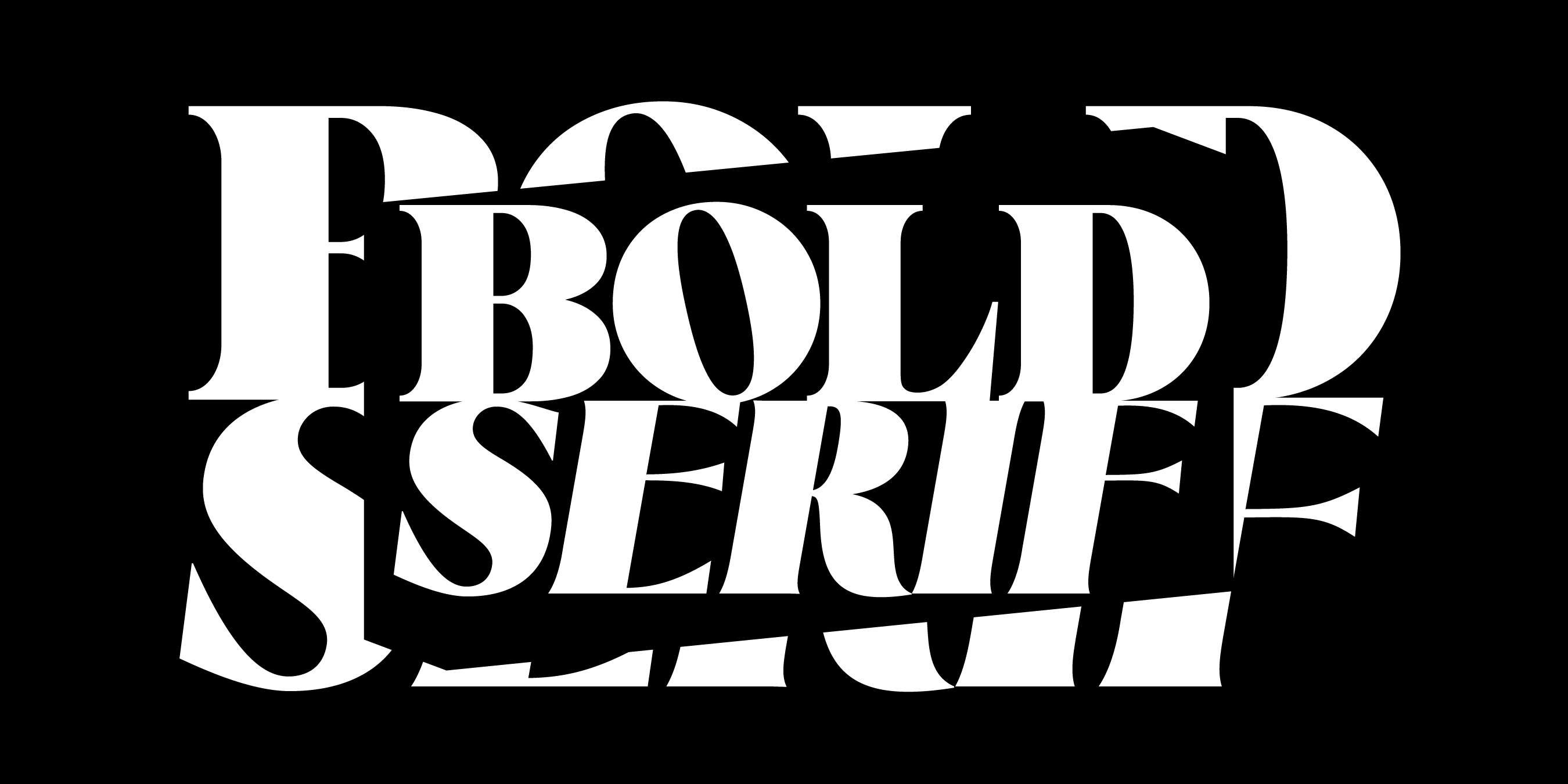
Wo Serifen stark sind: Diese fetten Serifenschriften stehlen allen die Show
Where Serifs Stand Strong: Bold Serif Fonts That Steal The Show
In den letzten Jahren hat die Designwelt eine bemerkenswerte Wiedergeburt von Serifenschriften erlebt, die durch das Aufkommen des Maximalismus im Design beschleunigt wurde. Diese Wiederbelebung ist nicht einfach eine nostalgische Rückkehr zur Tradition, sondern ein strategisches Engagement für Persönlichkeit und Ausdruckskraft in der Typografie. Serifenschriften mit ihren charakteristischen „Füßen“ am Ende der Buchstaben bieten eine breite Leinwand für die Darstellung von Charakter – dank ihrer unterschiedlichen Formen und Umrisse können sie ein breiteres Spektrum an Tönen vermitteln als serifenlose Schriften .
Die einzigartigen Merkmale jeder Schriftart mit fetten Serifen können ihnen eine große Wirkung verleihen. Sie sind so konzipiert, dass sie den Raum selbstbewusst einnehmen und sowohl dominant (weil sie mehr Leerraum einnehmen) als auch nuanciert (weil sie mehr Zeilen zum Arbeiten haben) in ihrem Ausdruck sein können. Diese Schriftarten können von weich und bauschig reichen, was Wärme und Zugänglichkeit ausstrahlt, bis hin zu scharf und stark, was Selbstvertrauen und Solidität ausstrahlt. Diese Vielseitigkeit macht Schriftarten mit fetten Serifen zu unverzichtbaren Werkzeugen für Designer, die ihrer Arbeit Persönlichkeit verleihen möchten.
Während minimalistische serifenlose Schriftarten aufgrund ihrer Einfachheit im Fließtext weiterhin beliebt sind, glänzen fette Serifenschriften in Rollen, die Aufmerksamkeit erregen. Ob in Überschriften, Buchtiteln, Zitaten oder jedem Designelement, das hervorstechen soll, fette Serifen geben ein autoritäres Statement ab. Sie dienen als emotionaler Brennpunkt, ziehen den Blick des Betrachters auf sich und verankern die visuelle Hierarchie einer Komposition.
In einer Landschaft, in der Design nach einem Gleichgewicht zwischen Wirkung und Eleganz sucht, bieten fette Serifenschriften ein kraftvolles Medium für den kreativen Ausdruck und sorgen dafür, dass Botschaften nicht nur gesehen, sondern auch gefühlt werden.
In dieser Liste untersuchen wir zehn fette Serifenschriften aus unserem Schriftstudio, die diese Prinzipien verkörpern. Jede ausgewählte Schriftart kann ein Statement abgeben, eine Nische besetzen und Ihrem Design mehr Tiefe verleihen.
1. Edde, moderne Craft-Serife mit starken Schnitten
Edde, moderne Craft-Serif mit starken Schnitten
Neueste Serifenschrift in unserer Sammlung: Edde in fetteren Stärken wie Bold, Extrabold und Black.
2. Kontrast Soft mit runden Rundungen für einen flauschigen Look
Contrast Soft mit runden Rundungen für einen flauschigen Look
Bauhaus Soft in Schwarz.
3. Kijs Extrabold für einen organischen, weichen Stil
Kijs Extrabold für einen organischen, weichen Stil
Kijs in Extrafett.
4. Quil, moderne Schriftart mit kurzen Serifen
Quil, moderne Schriftart mit kurzen Serifen
Bauhaus Quil in Fettschrift.
5. Rozi mit scharfen, langen Serifen
Rozi mit scharfen, langen Serifen
Bauhaus Rozi in Extrabold.
6. Mod für ein zeitloses, klares Design
Bauhaus Mod für moderne Serifen
Bauhaus Mod in Fett, Extrafett und Schwarz.